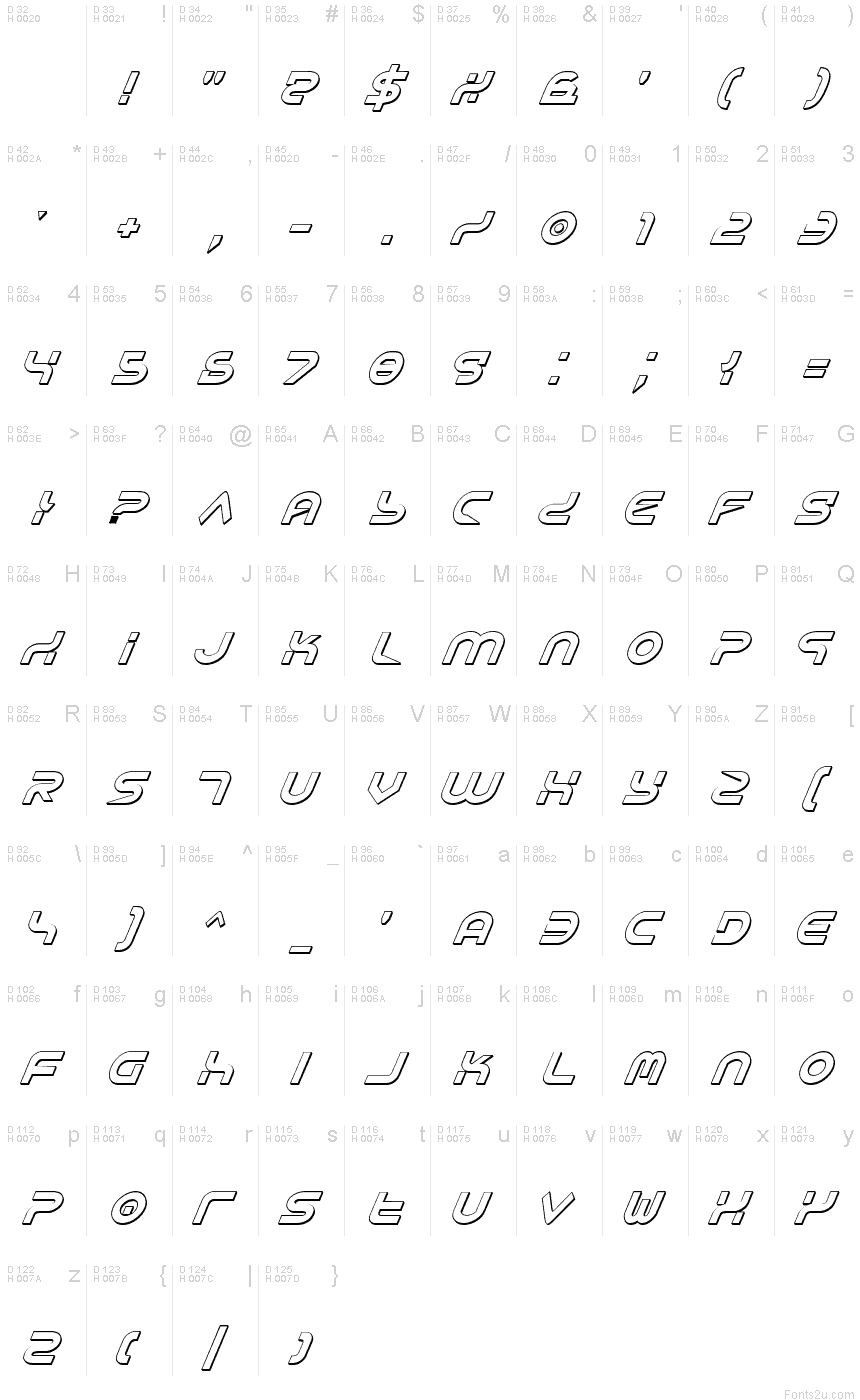
Yukon Tech Shadow Italic di Iconian Fonts è un font gratuito futuristico con effetto ombra, caratterizzato da un'inclinazione scattante e da lettere ampie e arrotondate. Le maiuscole ricordano l'hardware sci-fi retro in movimento, con un'ombreggiatura interna che dona alle forme un aspetto tridimensionale e definito, mantenendo intatto un ritmo fluido e compatto.
Si adatta perfettamente a loghi di videogiochi, poster arcade, grafiche synthwave, eventi tecnologici e titoli dove è richiesto un font gratuito veloce e con un tocco di estetica cromata. Poiché le lettere sono larghe, semplici e dotate di una profondità integrata, il font è ideale anche per brevi titoli e monogrammi che devono colpire nel segno senza bisogno di ulteriori effetti.